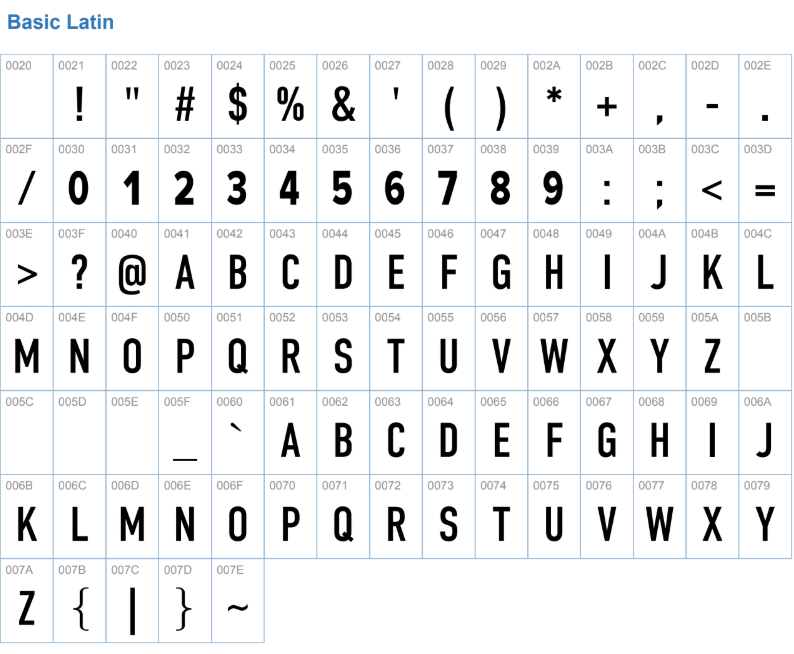
A camisa com a faixa vermelha cruzada no peito é um dos ícones mais pesados do futebol mundial. Para a temporada 2025-2026, a parceria histórica entre o River Plate e a Adidas renova o visual dos Millonarios com uma tipografia que exala modernidade sem perder a classe.
Se você trabalha com personalização de camisas ou design esportivo, sabe que ter a fonte correta é o detalhe que separa uma réplica comum de um trabalho de nível profissional. Disponibilizamos aqui o arquivo exato usado nos uniformes titulares, reservas e de goleiro para o ciclo atual de competições da AFA e CONMEBOL.
Estilo Visual e Identidade
A nova fonte da Adidas para o River Plate segue a tendência global da marca alemã para a temporada, apostando em traços sólidos e alta legibilidade, essenciais para a visualização nos gramados do Monumental de Núñez.
O design apresenta números com espessura média e cortes geométricos sutis nas extremidades, conferindo um ar tecnológico e agressivo. Diferente de temporadas anteriores que usavam fontes mais “arredondadas”, a versão 2025/26 traz uma estética mais industrial e limpa. Ela se destaca perfeitamente tanto sobre o branco clássico da camisa titular quanto nos tons escuros dos uniformes alternativos.